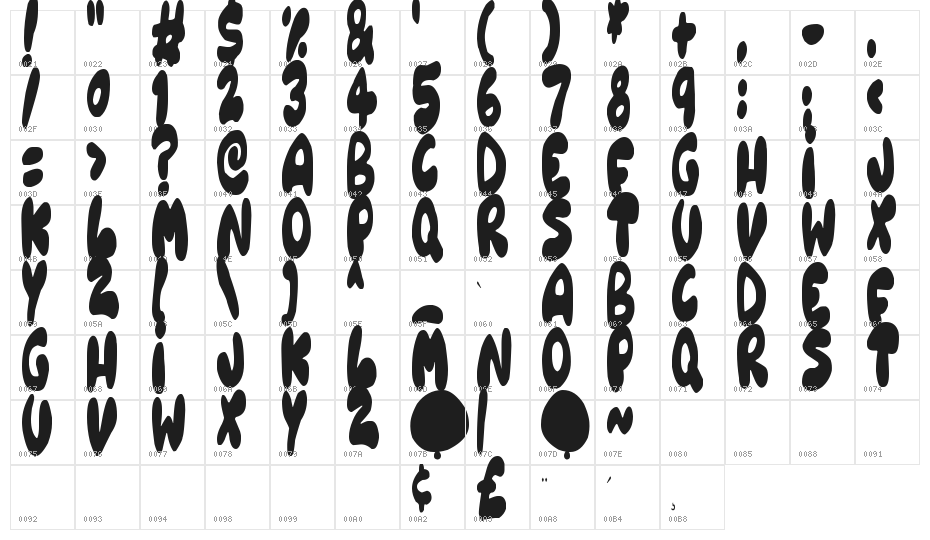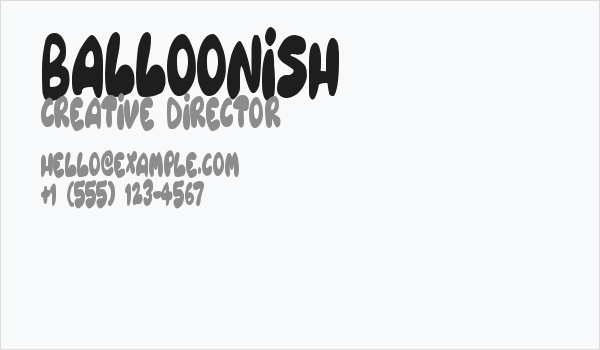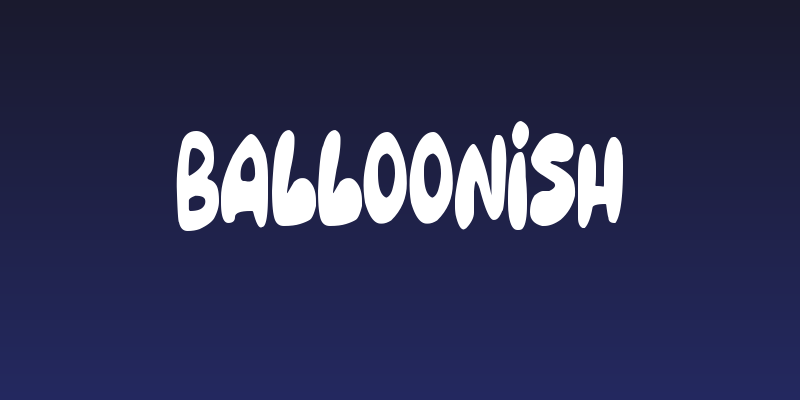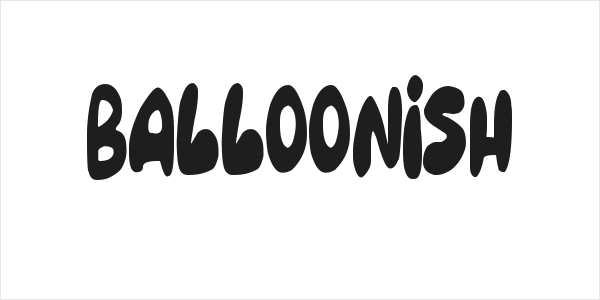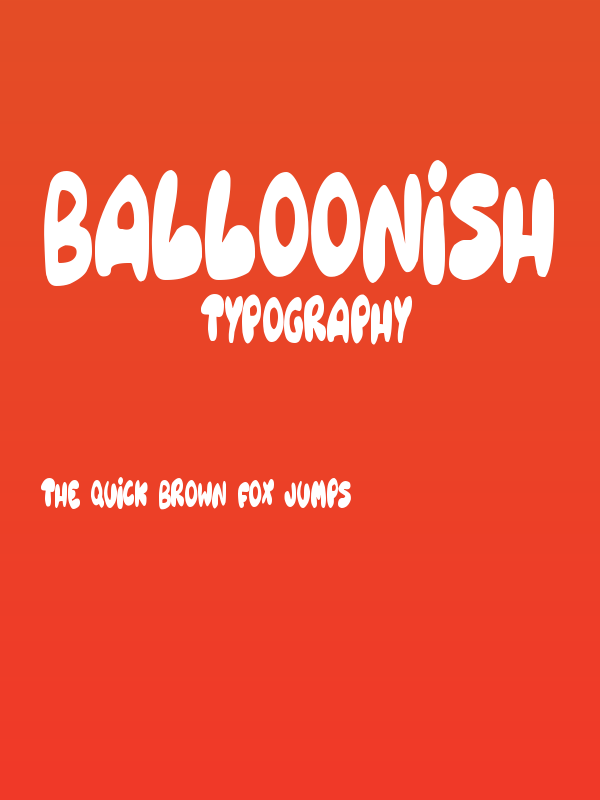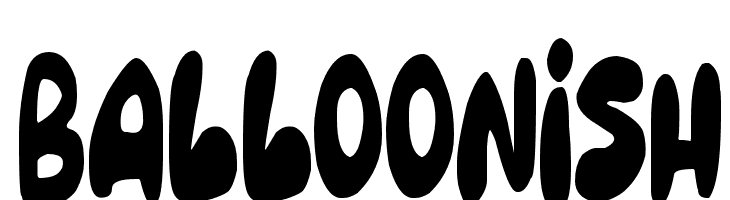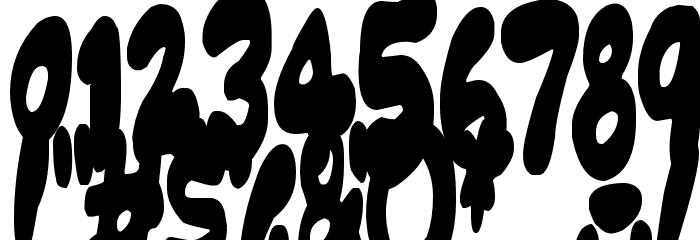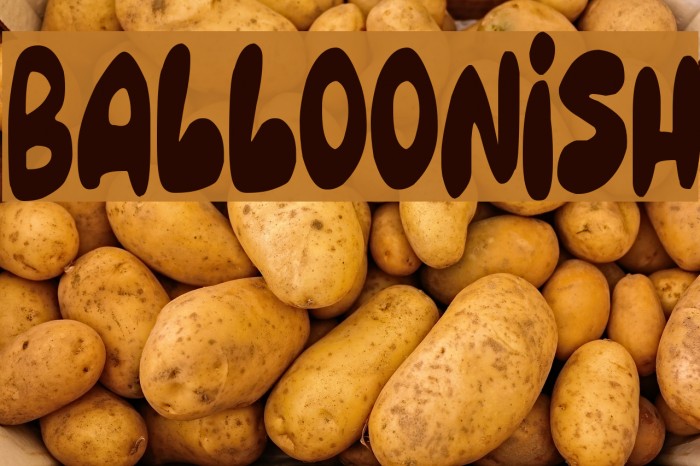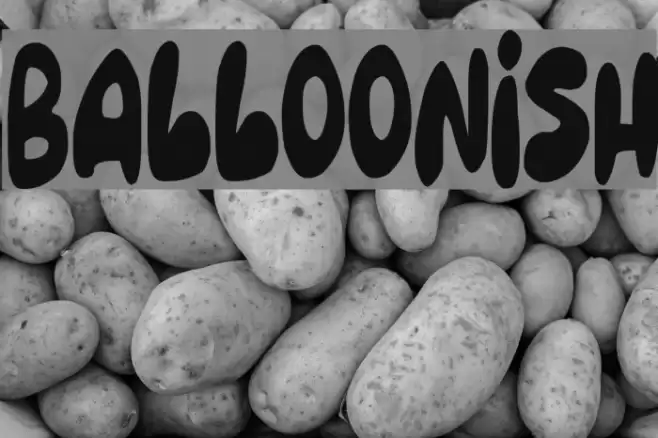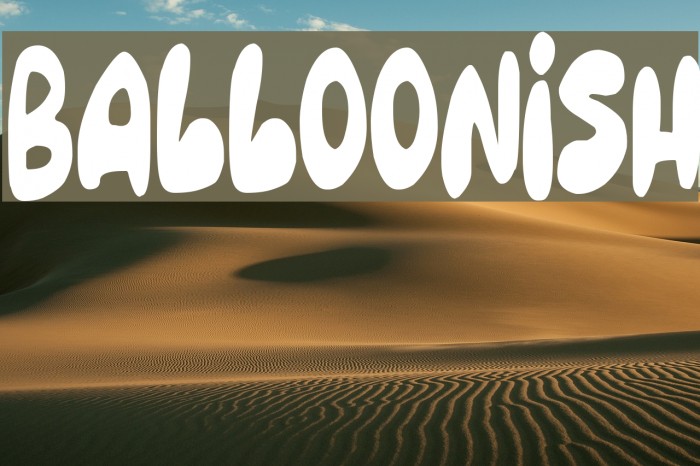
Balloonish Font
| Estilo geral | Playful, Whimsical |
| Projetos propostos | Ideal for children's books, party invitations, playful branding, and any project needing a fun and whimsical touch. |